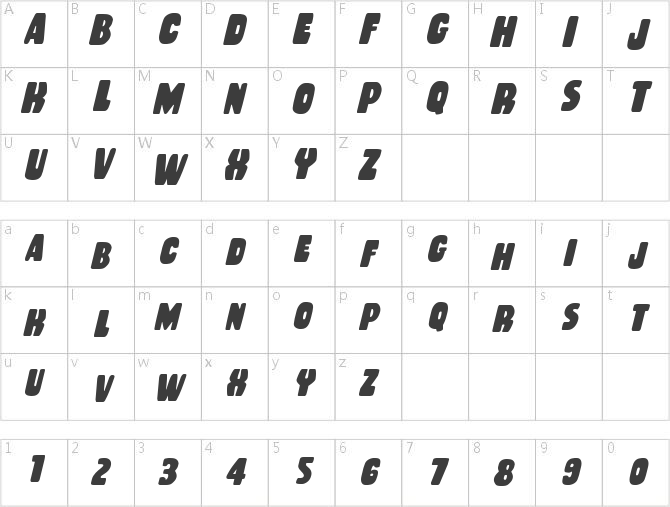
rubberboycondital 詳情頁(yè)
rubberboycondital字體字庫(kù)是一款讓人賞心悅目、百看不厭的英文字體,適合各類廣告和產(chǎn)品包裝設(shè)計(jì)應(yīng)用,字體大小0.05MB,格式為ttf字體,上傳用戶是小猴子1003,作者/版權(quán)方為未知